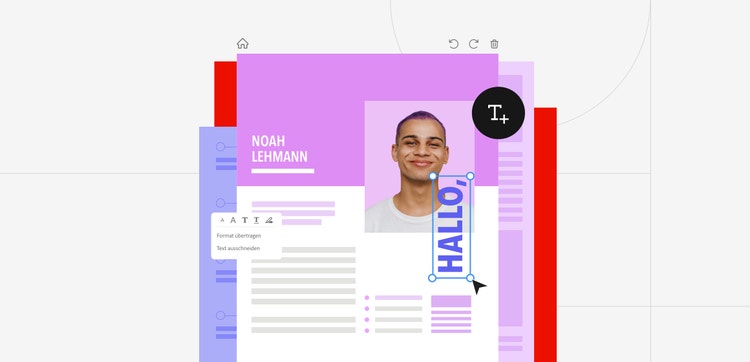
Die richtige Wahl von Schriftart und -größe ist essenziell, um deine Bewerbung optisch ansprechend und leserlich zu gestalten. Professionell gewählte Schrifteinstellungen unterstreichen den Inhalt deiner Bewerbung und sorgen dafür, dass wichtige Informationen klar und überzeugend präsentiert werden. In diesem Artikel erfährst du:
Die Gestaltung einer Bewerbung entscheidet darüber, welchen ersten Eindruck ein potenzieller Arbeitgeber von dem der Bewerber in erhält. Neben dem Inhalt der Unterlagen spielt auch die Optik eine entscheidende Rolle: Schriftart und -größe beeinflussen nicht nur die Lesbarkeit, sondern tragen maßgeblich zur Professionalität und zur Gesamtwirkung der Bewerbung bei. Eine gut gewählte, harmonische Schrift vermittelt Struktur und Ordnung und zeigt, dass du auf Details achtest.
Die Wahl der Schriftart und -größe spielt in einer Bewerbung eine wesentliche Rolle. Eine schlecht lesbare oder unprofessionell wirkende Schrift kann schnell vom Inhalt ablenken und einen ungewollt negativen Eindruck hinterlassen. Die richtige Gestaltung der Bewerbung trägt nicht nur zur Übersichtlichkeit bei, sondern vermittelt auch ein Bild von Sorgfalt und Detailgenauigkeit – Qualitäten, die in fast jeder Position gefragt sind.
Ein zentraler Punkt dabei ist die Lesbarkeit: Eine gut zu lesende Schriftart erleichtert den Lesefluss und steigert das Verständnis. Klare, professionell wirkende Schriften sorgen dafür, dass sich der die Leser in besser auf den Inhalt konzentrieren kann, ohne sich durch verschnörkelte oder zu kleine Texte kämpfen zu müssen. Besonders in langen Textabschnitten wie dem Motivationsschreiben oder dem Anschreiben ist eine lesefreundliche Schrift entscheidend, um die wichtigsten Informationen schnell zu erfassen.
Schriftart und -größe beeinflussen zudem, wie du auf Personalverantwortliche wirkst: Eine gut gewählte Schrift zeigt Professionalität und wirkt sich positiv auf das Gesamtbild aus. Schriftarten wie Times New Roman oder Arial, die als Standards gelten, vermitteln einen seriösen Eindruck und sind durch ihre Bekanntheit im beruflichen Kontext leicht zu verarbeiten. Moderne, zurückhaltende Schriftarten wie Calibri oder Helvetica wirken frisch und strukturiert und vermitteln einen innovativen, professionellen Eindruck.
Für Bewerbungsschreiben und Lebensläufe haben sich bestimmte Schriftarten als besonders geeignet herausgestellt, da sie eine gute Lesbarkeit mit einem seriösen Erscheinungsbild kombinieren. Dabei ist eine grundlegende Unterscheidung zwischen Serifenschriften und serifenlosen Schriften hilfreich, da beide Typen unterschiedliche Wirkungen haben und je nach gewünschter Ausstrahlung zum Einsatz kommen.
Serifenschriften zeichnen sich durch kleine „Füßchen“ an den Buchstaben aus und gelten als klassisch und seriös. Sie verleihen dem Text ein traditionelles und vertrauenswürdiges Aussehen. Besonders in konservativen Branchen wie Recht, Finanzen oder Verwaltung wird dies positiv aufgenommen.
Jede Schriftart hat ihre Stärken und Schwächen, die abhängig vom Einsatz und der Branche berücksichtigt werden sollten:
Tipp: Die Wahl zwischen Serifenschriften und serifenlosen Schriften hängt von der Branche und der angestrebten Position ab. In konservativen Branchen bietet sich eine klassischere Serifenschrift an, die Seriosität und Beständigkeit ausstrahlt. Für moderne, kreative oder technikorientierte Berufe kann eine klare serifenlose Schrift die richtige Wahl sein, da sie Offenheit und Innovation signalisiert.
Die Schriftgröße trägt ebenfalls zur Lesbarkeit und Struktur einer Bewerbung bei. Eine zu kleine Schrift erschwert das Lesen und hinterlässt einen unprofessionellen Eindruck. Eine zu große Schrift wiederum nimmt unnötig viel Platz in Anspruch. Daher ist es wichtig, die Schriftgröße in deinem Anschreiben oder Lebenslauf optimal anzupassen.
“Die Wahl der richtigen Schriftart für deine Bewerbung ist mehr als nur eine Stilfrage – sie ist Ausdruck von Präzision und Professionalität. Achte darauf, dass deine Schrift das Wesentliche deiner Bewerbung unterstützt: eine klare Kommunikation. Einheitlichkeit und Lesbarkeit sind dabei das A und O. Setze auf Schriften, die ruhig und professionell wirken, und wechsle innerhalb der Bewerbung nicht zwischen verschiedenen Schriftarten. So lenkst du die Aufmerksamkeit dahin, wo sie hingehört – auf deine Fähigkeiten und Erfahrungen.”
Neben Schriftart und -größe sind zusätzliche Formatierungsaspekte wichtig, um das Gesamtbild deiner Bewerbung und deines Lebenslaufs zu optimieren: